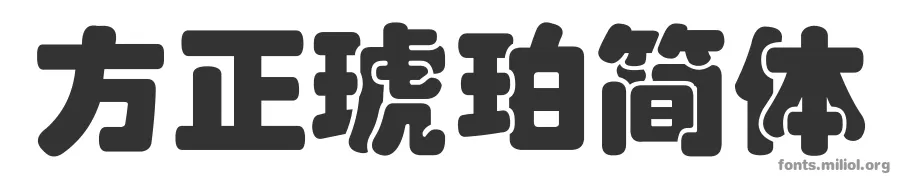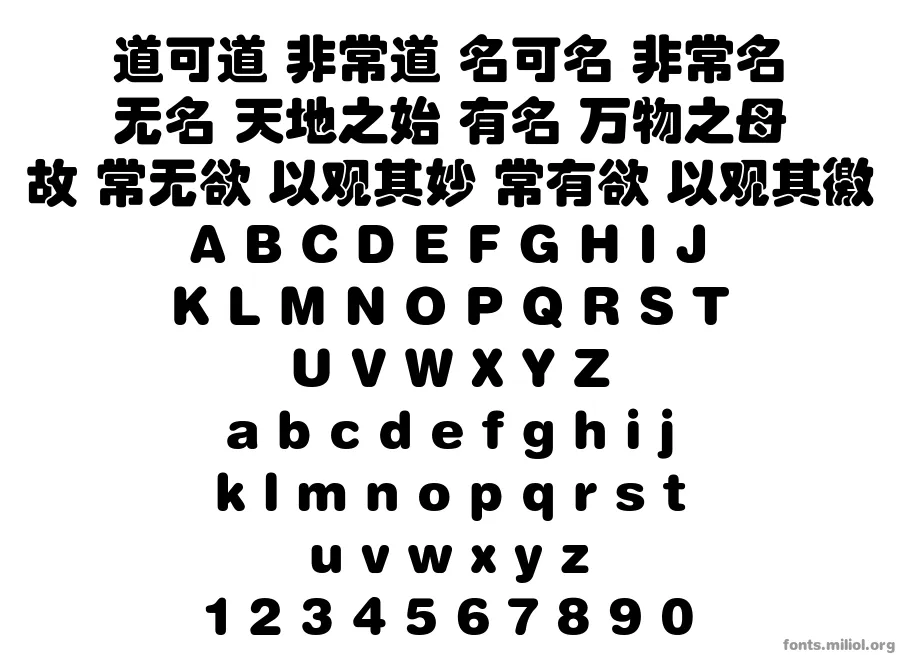
## 方正琥珀简体:圆润可爱的经典中文字体
方正琥珀简体是一款极具特色的中文字体,由北大方正电子有限公司设计开发。这款字体以其圆润饱满的笔画和活泼可爱的风格著称,每个字都像是由晶莹剔透的琥珀雕刻而成,散发着温暖而亲切的视觉魅力。
该字体最显著的特点是笔画末端都采用圆形处理,转折处也多为柔和的曲线,完全摒弃了传统字体中的锐利棱角。这种设计使得文字整体呈现出Q弹软萌的质感,特别适合用于儿童读物、卡通动漫、甜品包装等需要营造轻松愉快氛围的场合。字体的中宫较为宽松,字间距适中,保证了良好的可读性。
作为方正字库中的经典作品,方正琥珀简体支持GB2312字符集,包含6763个常用汉字和符号,能够满足日常中文排版需求。其独特的艺术风格既保留了汉字的基本结构,又通过创新的笔画处理赋予了文字新的生命力,是设计师手中不可多得的创意字体。